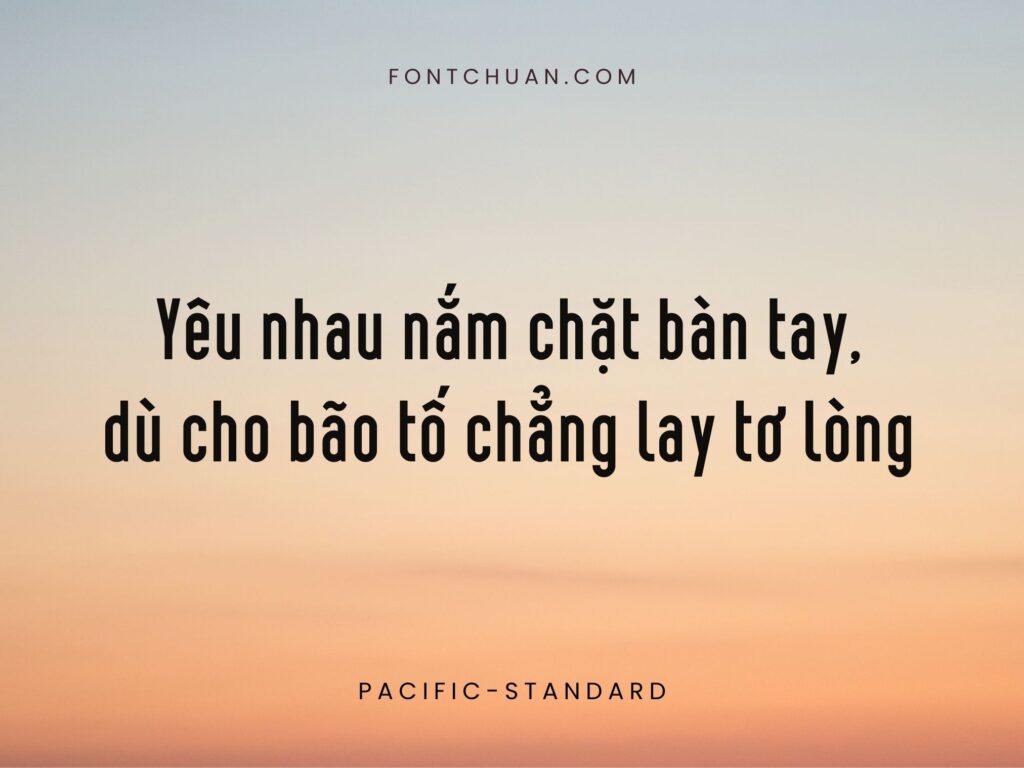
Font Pacific Standard+ Việt Hóa
Tác giả Font: Max Kisman
Pacific Standard là một font sans-serif được thiết kế bởi William Hastings và phát hành bởi Pacific Standard Type. Font này được thiết kế với mục đích sử dụng cho các tiêu đề và văn bản hiển thị, mang đến vẻ ngoài hiện đại và chuyên nghiệp. Nhờ phong cách tối giản, mạnh mẽ và dễ đọc, Pacific Standard cũng được đánh giá là một Font chữ bất động sản lý tưởng, giúp các ấn phẩm quảng bá dự án hay thương hiệu trong lĩnh vực này trở nên sang trọng và đáng tin cậy hơn. Pacific Standard hỗ trợ nhiều ngôn ngữ, được sưu tầm và đăng bởi thành viên của Font Chuẩn.
Font có cấu trúc chữ rõ ràng, độ dày nét đồng nhất và các đường nét tinh tế, tạo nên sự cân bằng giữa tính thẩm mỹ và khả năng đọc. Pacific Standard phù hợp cho các thiết kế liên quan đến thương hiệu, truyền thông xã hội, tiêu đề và nội dung số. Các ngành nghề như quảng cáo, công nghệ, giáo dục và bất động sản có thể tận dụng hiệu quả font này. Ngoài ra, Pacific Standard cũng thích hợp cho các sự kiện như lễ hội, sinh nhật, ngày Nhà giáo và Valentine.